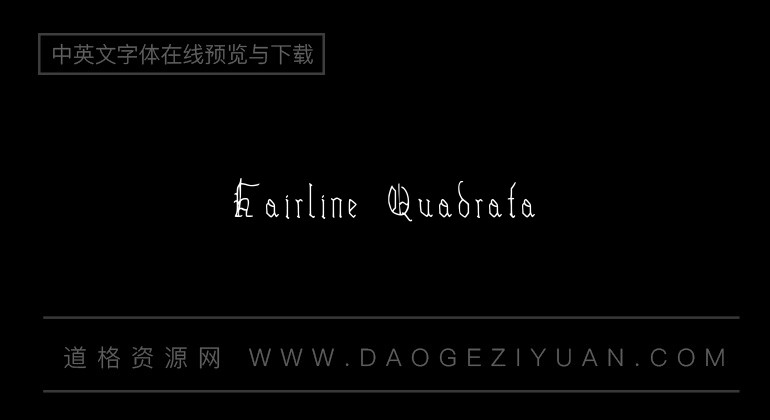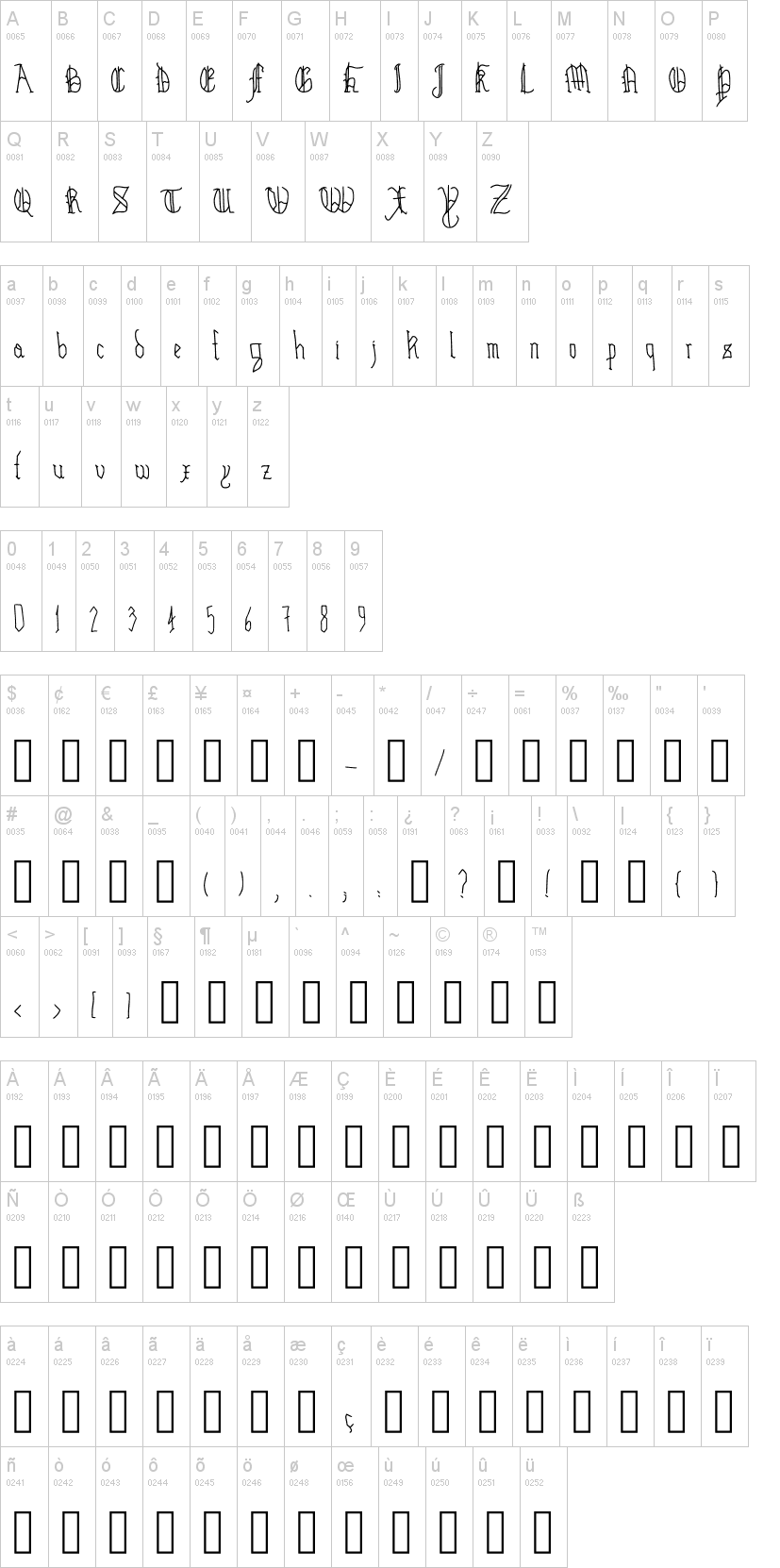
? Hairline Quadrata 字体是一款细线框字体,它具有细节丰富的外观,属于细线框字体的一种,其字形设计精细,模糊的线条使字体更加柔和,适用于新闻、广告和出版物等。它的字体特性是它具有精细的细线框,可以提供出色的可读性,并且可以让文字看起来更加轻巧,而且可以提供出色的可读性,可以使文字看起来更加轻巧。内容介绍
Hairline Quadrata是一款非常不错的手写艺术字体,具有很好的视觉感,适合于文化类的宣传设计、商业类品牌的广告和产品包装设计以及个性化文字排版等较多场景。